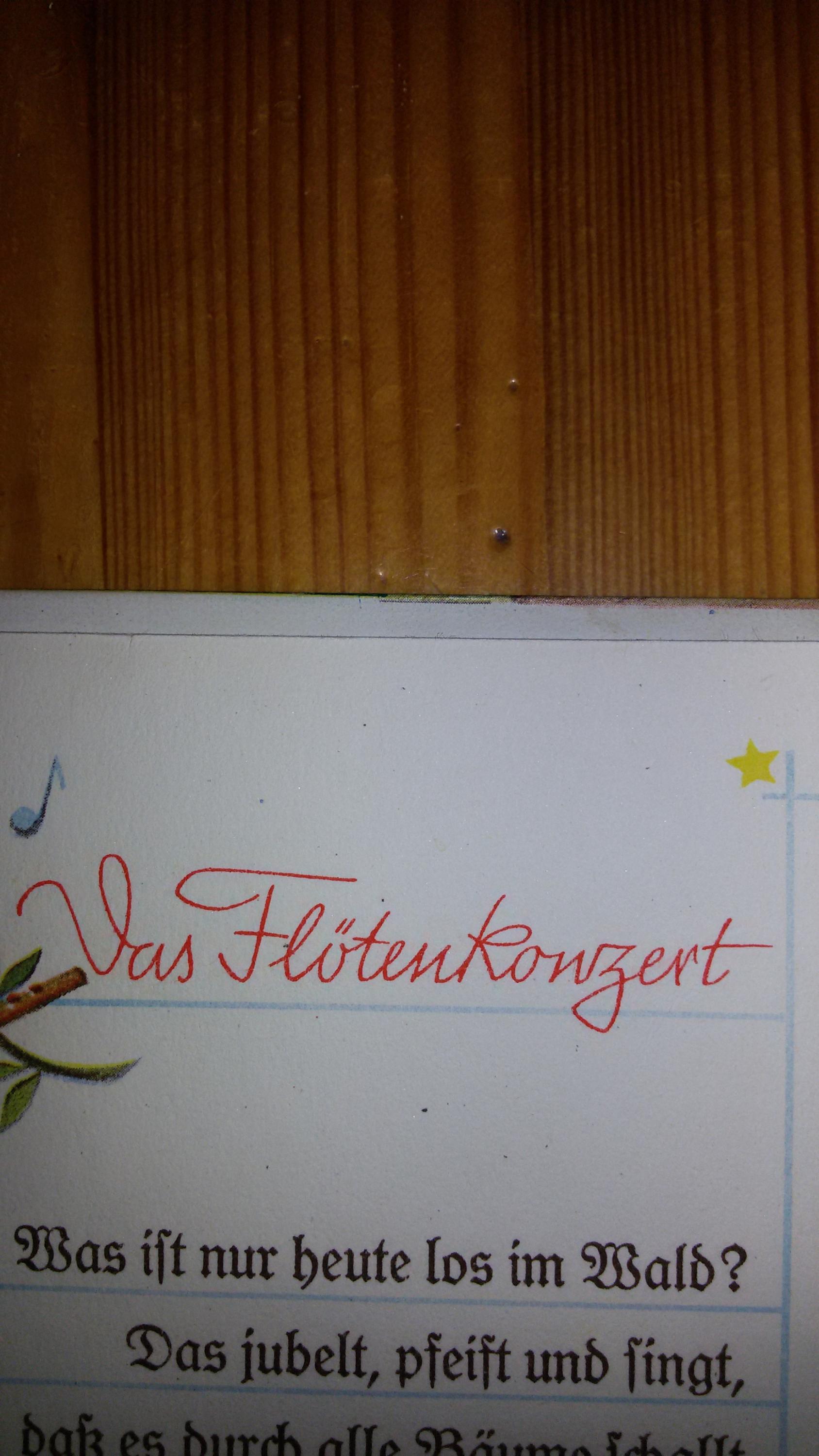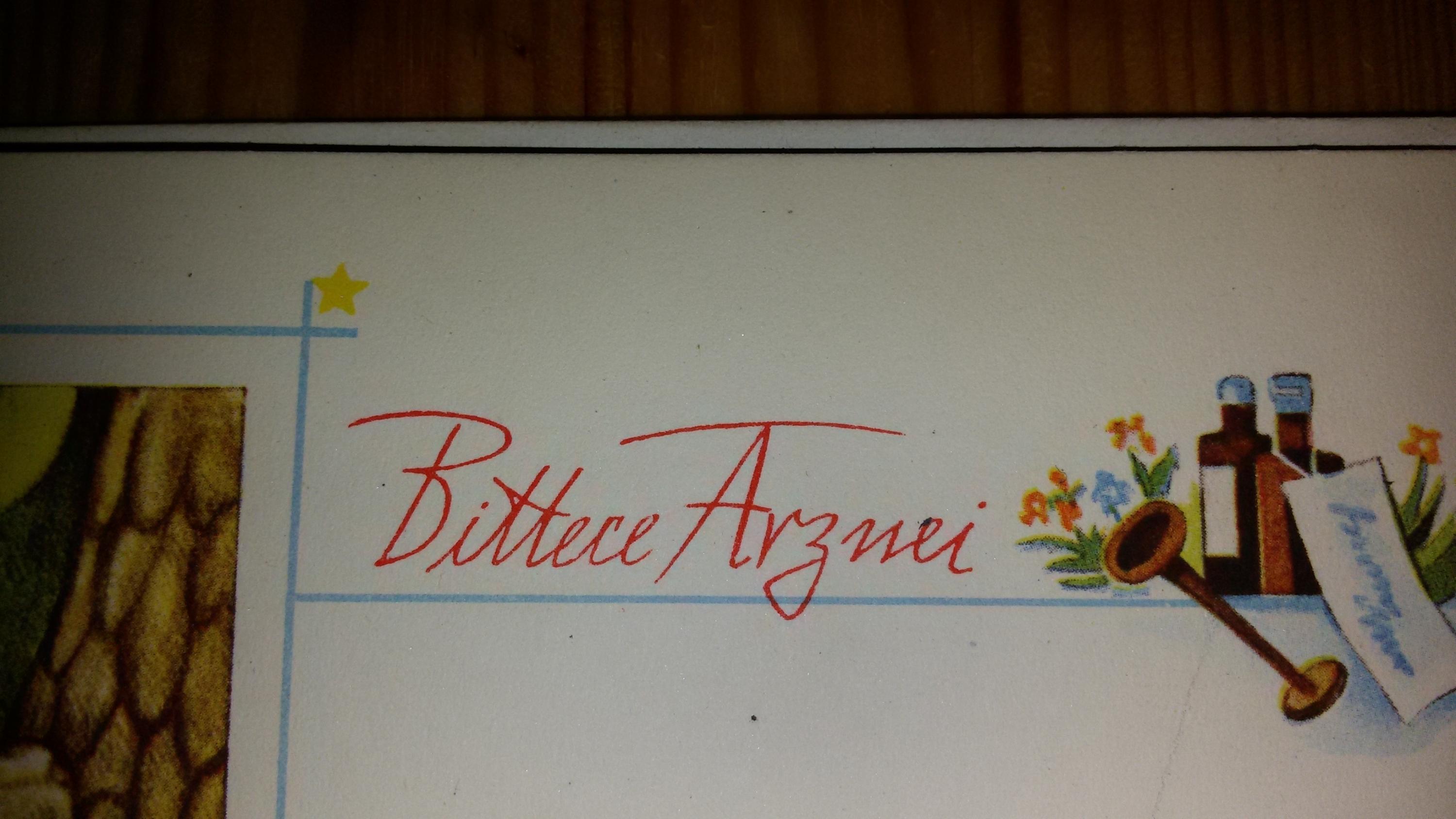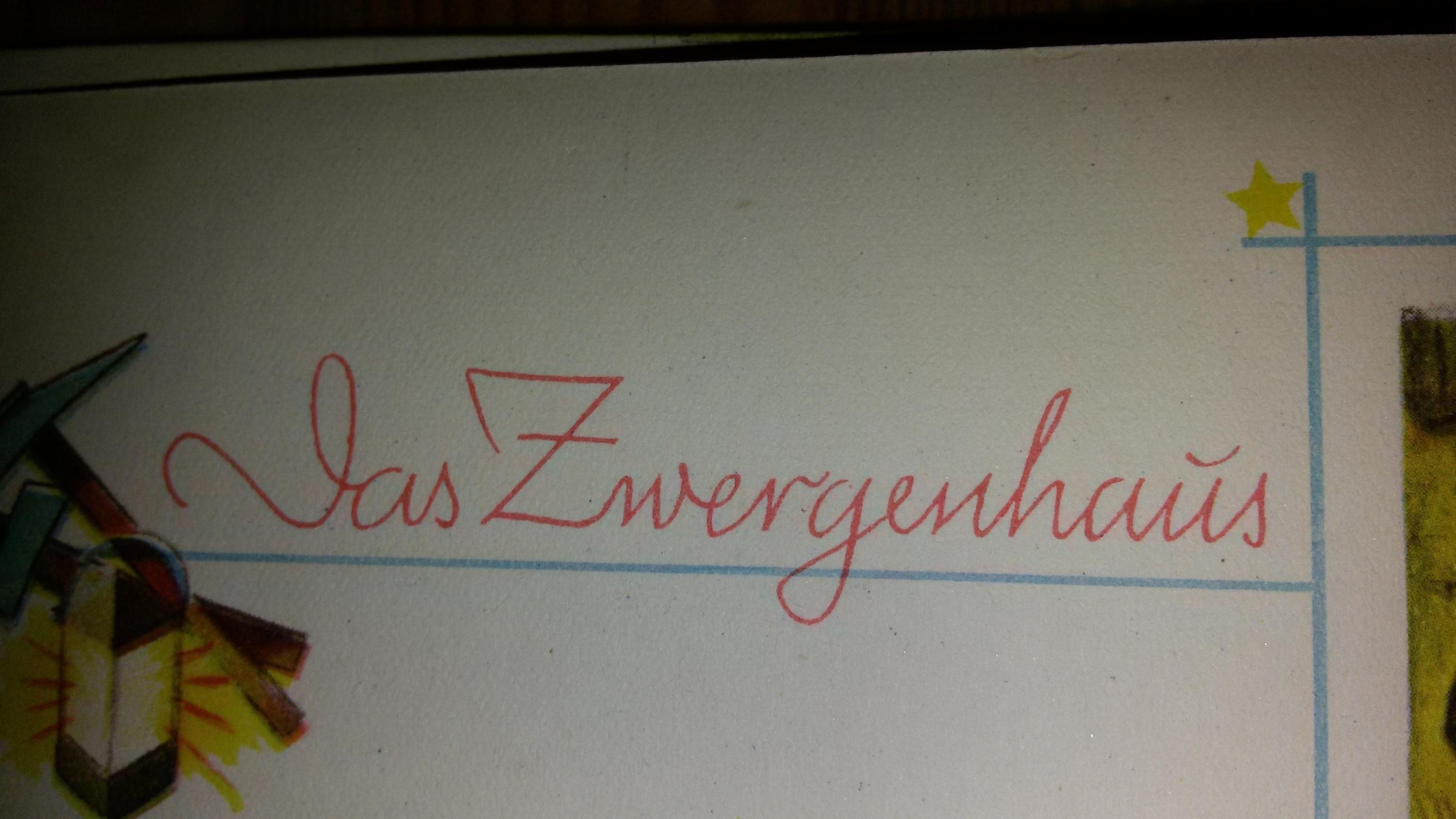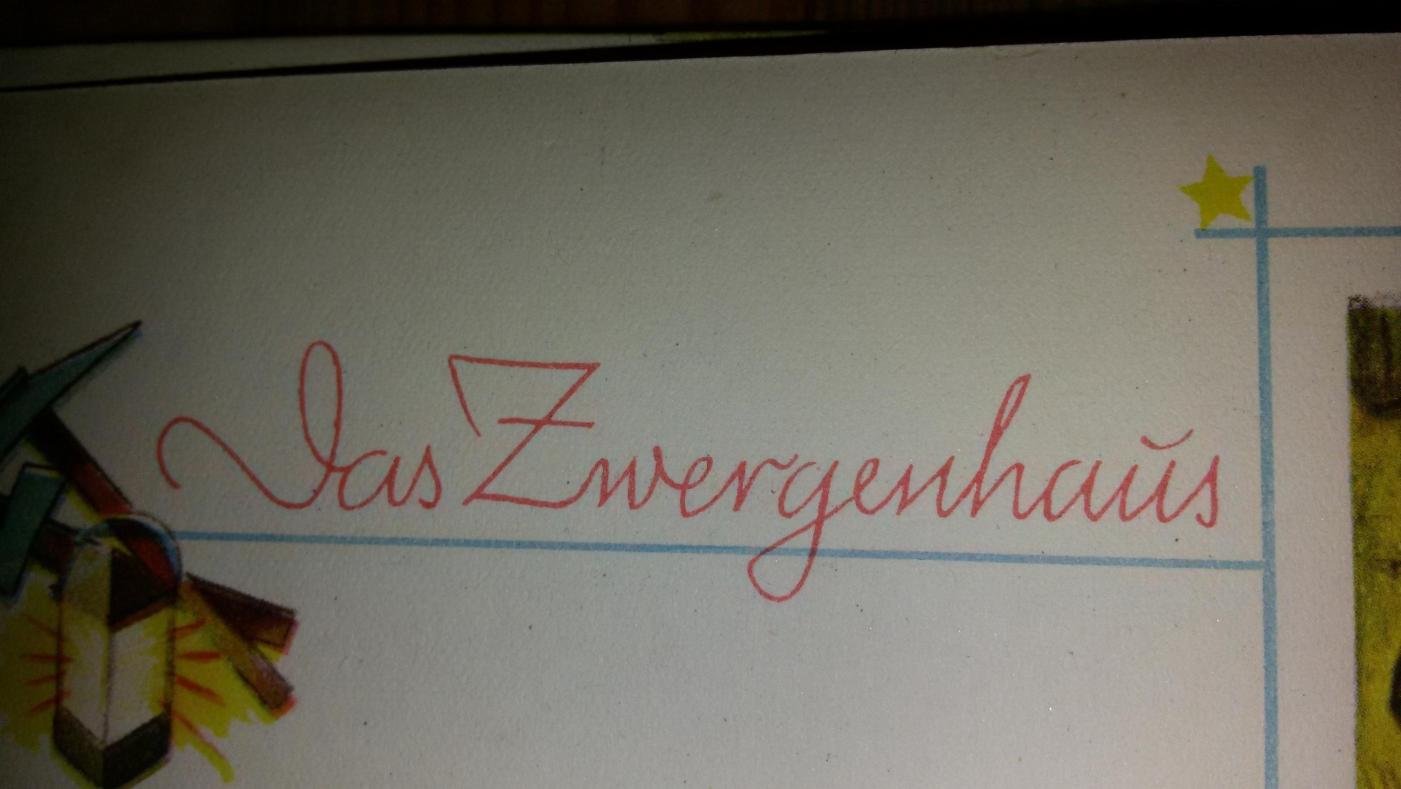
Schrift aus Buch Allerlei aus dem Zwergenreich
Sind diese Schriften wohl auch Lettering-Arbeiten? Sie sind aus dem Buch "Allerlei aus dem Zwergenreich" von Onkel Ernst, ;-) aus dem Jahr 1940.
Sobald Du beim Vergleichen identischer Buchstaben einen unterschied erkennen kannst, ist die Wahrscheinlichkeit für Handgeschriebenes sehr hoch. Zwar ist es durchaus möglich über OpenType-Funktionen eine verbundene Handsxchrift recht gut zu simulieren, wie es im Zwergenhaus mit den unterschiedlichen Koppelpunkten zu berücksichtigen, aber wenn dann der selbe Buchstabe in gleicher Umgebung wieder erscheint, wird er tatsächlich selbst sehr sauber geschrieben, kleine Veränderungen haben, dass du nie 100% identische Buchstaben finden wirst.
Ein Beispiel für so eine automatische verbundene Schreibschrift: Meine Schriftart EuroScript
Zumal das "D" in Sütterlin geschrieben ist. Eine Satzschrift mit grundsätzlich lateinischen Buchstaben und einzelnen in Sütterlin ist höchst unwahrscheinlich.
Zumal das "D" in Sütterlin geschrieben ist.
Ähm, Sütterlin? Das ist so, als würde man bei jeder Serifenlosen sagen, das wäre Arial, und bei jeder Serifenschrift, das es Times ist.
Sütterlin ist nicht die generische Schriftklasse, sondern die sehr aufrecht geschriebene Schul-Ausgangsschrift von Ludwig Sütterlin.
Dies ist Sütterlin:
und auch das ist Sütterlin:
Und das ist Rudolf Kochs Offenbacher Schrift, und eben kein Sütterlin, auch diese wurde in der letzten Zeit, als noch deutsche Schreibschrift gelehrt wurde statt der von Sütterlin an Schulen verwendet:
Und ich glaube, das D stammt eher aus der Offenbacher.
Ja ja, ich weiß, Begriffsmonopole wie Tesafilm, Tempotücher und eben Sütterlin sind kaum zu umgehen...
Da hast du vollkommen Recht.
Ich korrigiere mich also und sage "Eine Satzschrift mit grundsätzlich lateinischen Buchstaben und einzelnen Nicht-Lateinischen ist höchst unwahrscheinlich."
Und dem kann ich dann nur zustimmen. Auf Dafont.com gibt es über 10000 Schriftarten aus dem Bereich Schreibschriften, darunter ist nicht eine mit diesem Merkmal. Allerdings habe ich bei Menschen, die noch sowohl eine deutsche Schreibschrift wie auch eine lateinische gelernt haben, solch einen Mix, bei dem der Schreiber sich aus beiden Schriftsystemen die angenehmsten Buchstaben heraus gesucht hatten, um so ihre persönliche Handschrift zu formen, schon einige male gesehen. Insbesondere einnere ich mich, dieses D in Leuchtreklamen der 1960er Jahre gesehen zu haben.